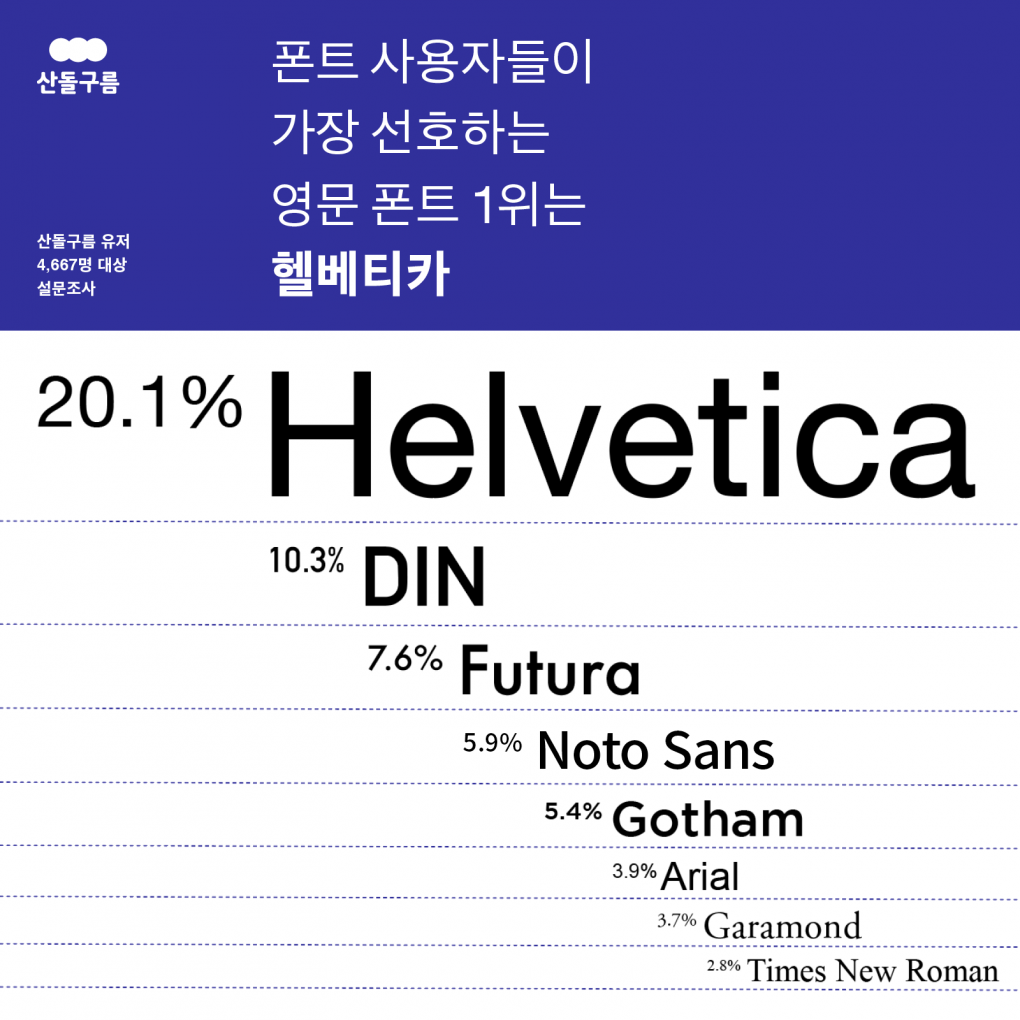
우리나라 폰트 사용자들이 가장 좋아하는 영문서체 2위는 DIN, 1위는?
우리나라 폰트 사용자들은 영문 폰트 중 헬베티카(HELVETICA)를 가장 선호하는 것으로 조사됐다.
폰트 회사 (주)산돌이 자사 클라우드 폰트 서비스인 산돌구름 유저 4,667명을 대상으로 ‘영문 폰트 사용 실태’에 대해 조사한 결과 20.1%가 헬베티카를 가장 많이 쓴다고 답했다. 헬베티카는 스위스의 막스 미딩거(Max Miedinger)가 1957년 디자인한 산세리프 서체로 BMW, 노스페이스, 맥도날드, 무인양품 등 다양한 브랜드가 사용하고 있기도 하다.
뒤를 이어 이성적이고 현대적인 감성의 산세리프 서체인 딘(DIN)DL 2위(10.3%), 나이미, 폭스바겐의 서체로 유명한 푸투라(FUTURA)가 3위(7.6%)를 차지했다.
또한 한글과 영문을 조합하여 사용할 때에 가장 선호하는 조합을 묻는 질문에는 ‘산돌고딕과 헬베티카(1.94%)’, ‘윤고딕과 헬베티카(1.2%)’, ‘본고딕과 고담(0.5%)’, ‘SM신신명조와 가라몬드(0.3%)’ 등 유저들의 성향이 반영된 다양한 답변이 나왔다. 별도의 영문 폰트를 선택하지 않고 ‘그때그때 다름(0.7%)’, ‘구분해서 사용하지 않음(0.5%)도 있었다.
한글과 영문을 조합해 사용할 때 무엇을 가장 중요하게 보는가에 대한 질문에는 ‘형태의 유사성’이 45.3%로 가장 많았다. 이어 ‘글자 높이(20.9%)’, ‘글자 너비(13.8%)’, ‘웨이트(8.6%)’, ‘속공간(7%)’ 순으로 조사됐다.
한편 새로운 영문 폰트가 필요할 때에는 ‘해외 폰트 사이트(43%)’를 가장 먼저 방문한다는 답변이 가장 많았으며 ‘포털 검색(32.2%)’, ‘지인이나 동료의 추천(11.7%)’, 국내 폰트 사이트(5.7%)’의 도움을 받는다는 답변도 있었다.
산돌 관계자는 “재미있는 것은 유저들이 선호하는 영문 폰트가 대부분 산세리프 계열의 폰트라는 점”이라며 “최근 들어 많은 글로벌 브랜드들이 자사 로고를 산세리프 폰트로 바꾸고 있는데, 폰트 사용자들의 취향에도 이와 같은 경향이 반영되는 것 같다”고 말했다.